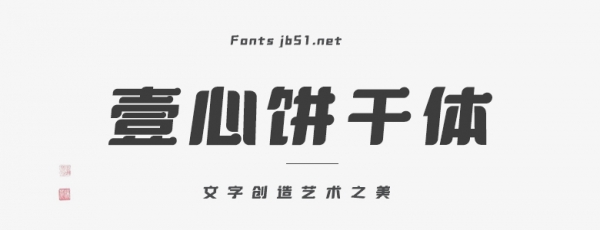
壹心餅干體是一款簡(jiǎn)約時(shí)尚的創(chuàng)意字體,適合應(yīng)用于藝術(shù)設(shè)計(jì)、平面宣傳設(shè)計(jì)、網(wǎng)頁(yè)設(shè)計(jì)、書法字體,海報(bào)設(shè)計(jì)等領(lǐng)域,歡迎喜歡這款字體的朋友下載收藏